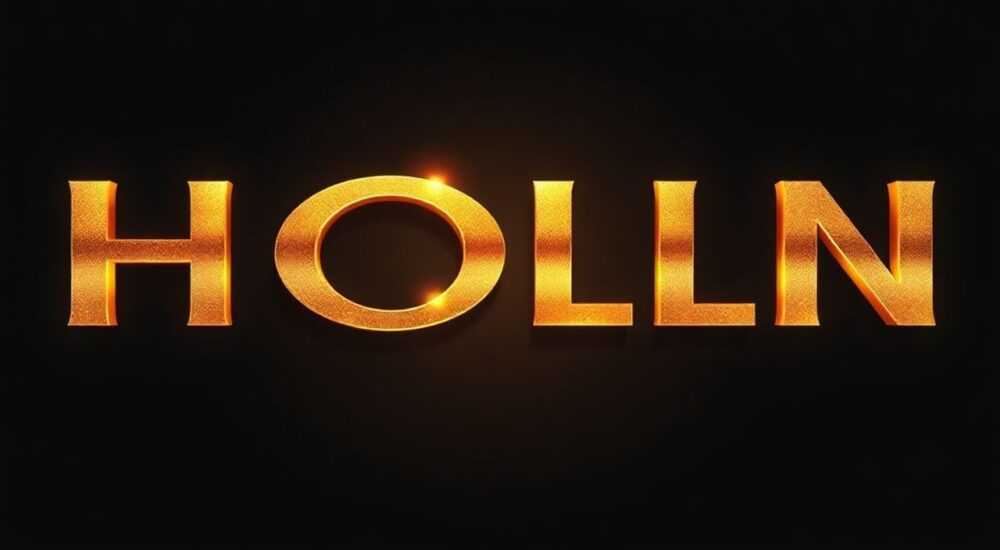
Как сделать золотой шрифт в фотошопе
Создание золотого шрифта в Photoshop — один из самых востребованных приёмов в графическом дизайне. Такой эффект применяется в рекламе, брендинге, оформлении премиальных продуктов и праздничных открытках. Золото ассоциируется с роскошью, успехом и высокой ценностью, поэтому умение реалистично имитировать металл даёт дизайнеру серьёзное конкурентное преимущество. Однако многие сталкиваются с проблемами: плоский результат, отсутствие объёма, нереалистичные блики или трудности с настройками материалов.
Основные методы создания золотого эффекта
Если вы хотите, чтобы текст выглядел действительно дорого, недостаточно просто покрасить его в жёлтый. Настоящее золото — это игра света, микротекстура, отражения и переливы. В Photoshop есть несколько подходов к достижению такого эффекта. Самый распространённый — использование стилей слоя. Он быстрый, не разрушает исходный текст и легко редактируется.
Другие методы включают рисование вручную с помощью кистей, применение готовых экшенов (Actions) и 3D-рендеринг через функцию 3D Extrusion. Первые два варианта хороши для массового использования, особенно если вы создаёте логотипы или элементы UI. Третий — для максимального реализма, но требует мощного ПК и времени на рендер.
Представьте, что вы работаете над упаковкой дорогих духов. Клиент хочет, чтобы название бренда «горело» на флаконе, как настоящее 18-каратное золото. Простое наложение цвета здесь провалится. Вам нужно моделировать объём, блики, тени и даже микротрещины поверхности. Именно поэтому профессионалы комбинируют несколько техник: стиль слоя + ручная проработка кистями + внешняя текстура.
Пошаговая инструкция: создать золотой шрифт
Начнём с базового, но эффективного способа — с использованием стилей слоя. Этот метод подходит новичкам и гарантирует достойный результат без лишних усилий.
- Откройте Photoshop и создайте новый документ (рекомендуемый размер — 1920×1080 px, 300 dpi для печати).
- Выберите инструмент Текст (T), кликните по холсту и введите нужную фразу. Шрифт лучше выбрать жирный, с засечками или без — главное, чтобы он был читаемым и объёмным (например, Baskerville, Playfair Display или Trajan Pro).
- Установите размер текста от 150 pt — чем крупнее, тем заметнее эффект.
- Щёлкните правой кнопкой по слою с текстом и выберите «Стиль слоя» → «Объём». Или нажмите на значок «fx» внизу панели слоёв.
- В открывшемся окне начните с пункта «Объём». Установите значение «Глубина» на 200–300%, чтобы придать тексту объём.
- Перейдите к «Градиентному контуру». Выберите градиент от тёмно-золотистого до светло-жёлтого. Можно использовать предустановленный градиент «Хром» или создать свой.
- Настройте «Блик»: угол освещения — 120°, непрозрачность — 75%, мягкость — 5 px. Это создаст естественный блик сверху.
- Добавьте «Тень от объёма»: расстояние — 5 px, размытие — 3 px, непрозрачность — 40%. Это закрепит текст на фоне.
Тонкости настройки стиля слоя
Многие останавливаются на стандартных настройках — и получают «игрушечное» золото. Чтобы добиться настоящего блеска, нужно углубиться в параметры. Например, в разделе «Контур» можно изменить форму перехода цвета. Выберите кривую с резким подъёмом — она имитирует резкий блик на гранях металла.
А вот в «Градиентном контуре» стоит экспериментировать с типом градиента. Линейный подойдёт для плоских поверхностей, радиальный — для выпуклых букв. Попробуйте градиент с несколькими цветовыми точками: тёмно-коричневый (10%), золотой (50%), светло-жёлтый (80%), белый (100%). Это воссоздаст отражение света на полированной поверхности.
Также важна настройка «Качество объёма». Убедитесь, что стоит «Высокое» разрешение. При низком качестве текст может «дрожать» при увеличении, особенно на экранах Retina.
Работа с градиентами и текстурами
Градиент — основа реалистичного золота. Но одного градиента недостаточно. Чтобы добавить живости, наложите текстуру. Это может быть сканированная поверхность настоящего золота, шум (Noise) или специальная PSD-текстура с микротрещинами.